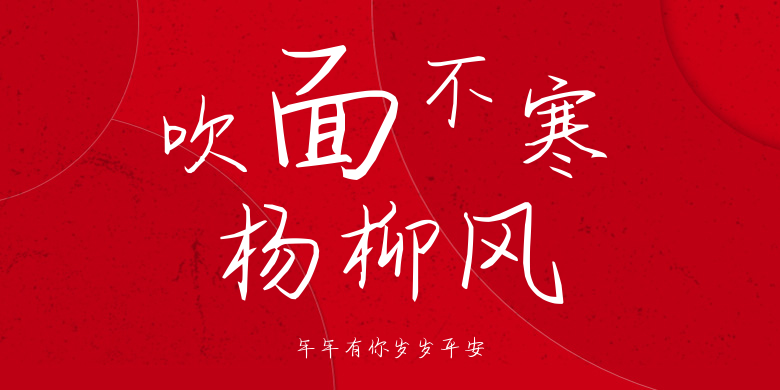
年年有你岁岁平安
年年有你岁岁平安,这款字体结构工整、笔画清晰,兼顾美观与易读性,适用于标题、正文、海报、包装、LOGO 等多种场景。字形优雅稳定,风格百搭耐看,适配日常排版与创意设计,让文字呈现更舒适、更具质感。年年有你岁岁平安一笔一画,皆是细节,以均衡的比例、流畅的线条打造舒适视觉体验,字形端正大气,风格简约现代。无论是商业设计、品牌宣传还是日常排版,都能轻松驾驭,让文字更有格调与力量。年年有你岁岁平安字体下载。